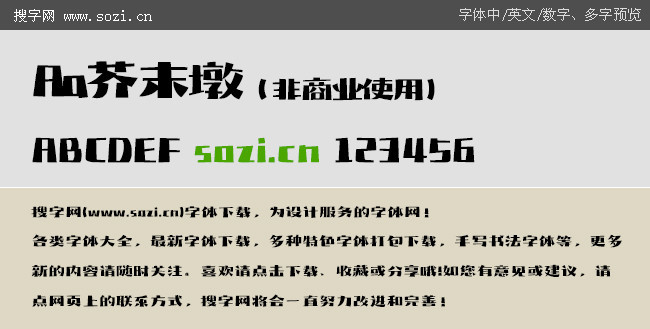
Aa芥末墩
搜字網(wǎng)給大家提供一款A(yù)a芥末墩(非商業(yè)使用)中文字體下載,該字體是一款非?蓯鄱睾竦乃囆g(shù)字體。在筆畫中融入柔和的線條處理增添了字體的親和力,通過(guò)對(duì)部分筆型的特殊處理,使字面空間分布更加均勻,適合應(yīng)用于藝術(shù)設(shè)計(jì)、平面宣傳設(shè)計(jì)、網(wǎng)頁(yè)設(shè)計(jì)、海報(bào)設(shè)計(jì)等應(yīng)用(此字體為個(gè)人非商用版,商用可以聯(lián)系QQ:1006760504)。